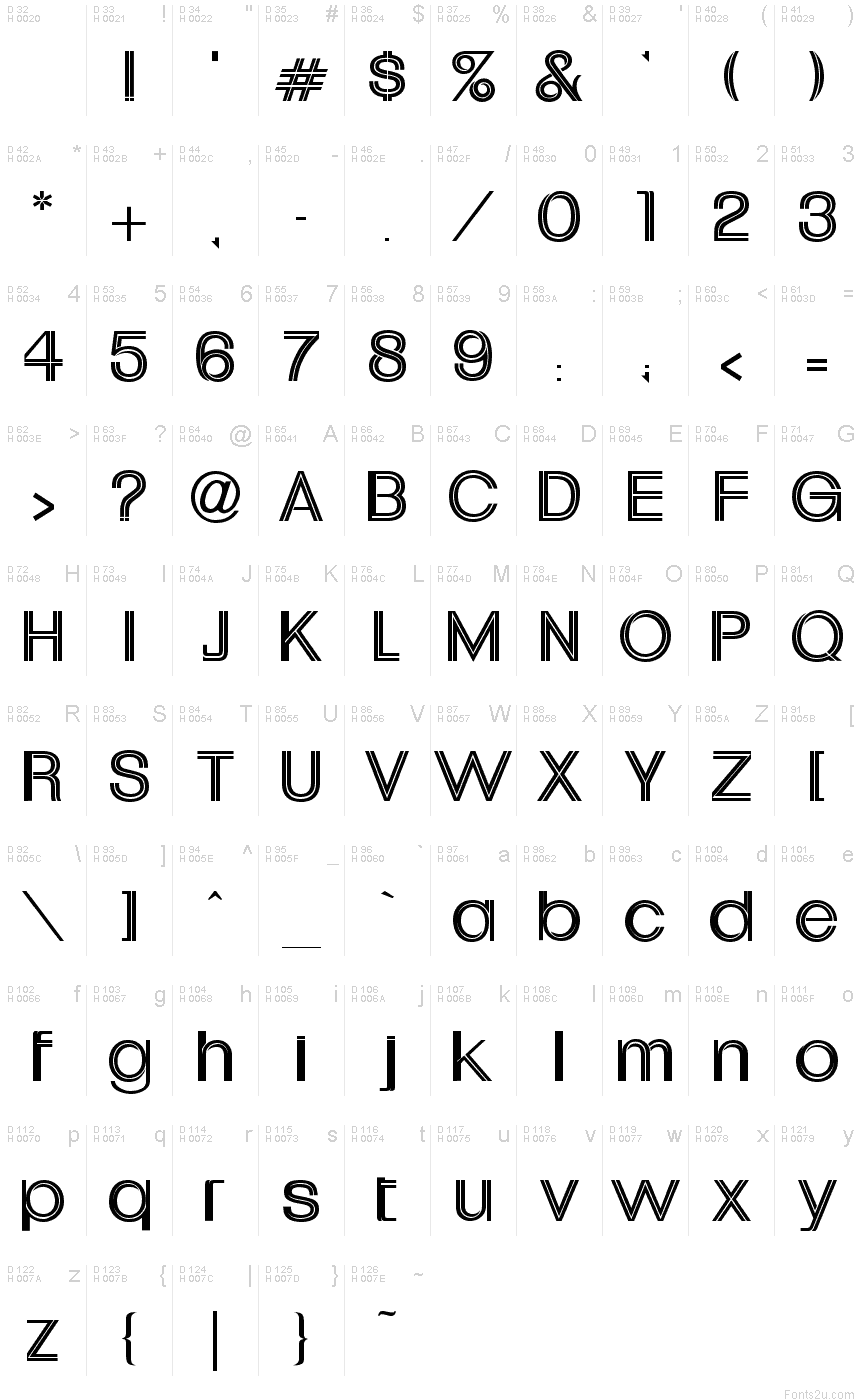
Uptight autorstwa A. Carra to darmowy, groovy krój typu display, utrzymany w eleganckim klimacie lounge końca lat 60. Litery opierają się na wysokich, zaokrąglonych formach i cienkich, równoległych liniach, dzięki czemu napisy sprawiają wrażenie lekkich i lekko psychodelicznych, ale nie przesadzonych.
Sprawdza się wszędzie tam, gdzie chcesz podkreślić ten fajny retro charakter – okładki płyt, tytuły na plakatach, opakowania butikowe, identyfikacja wizualna kawiarni czy nagłówki w magazynach to idealne zastosowania dla tego darmowego fontu. Dzięki wydłużonym i zapętlonym kształtom szczególnie dobrze sprawdza się w krótkich nazwach, planszach tytułowych i logotypach typu monogram, gdzie rytm liter powinien pozostać otwarty i wyraźny.
Uptight